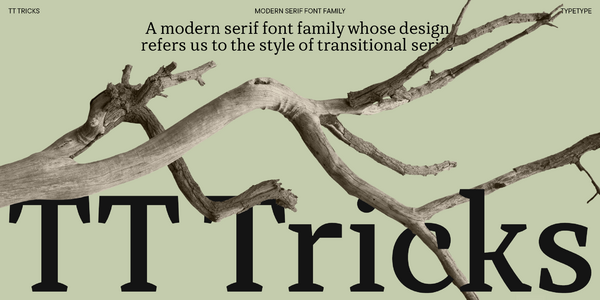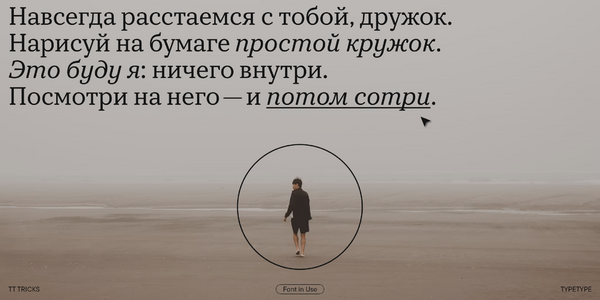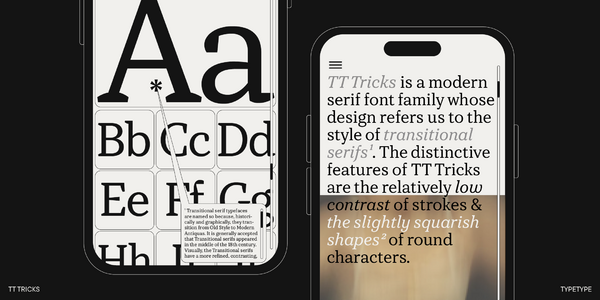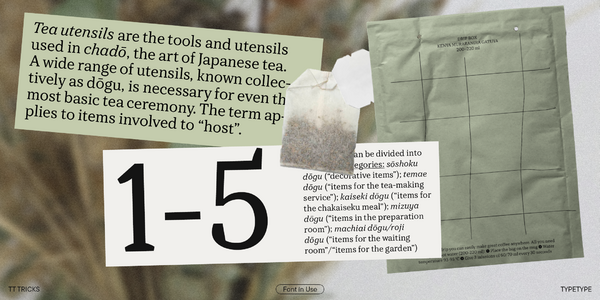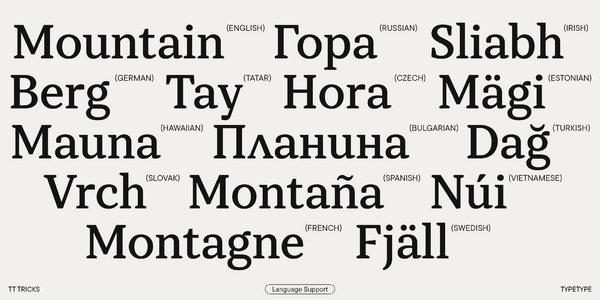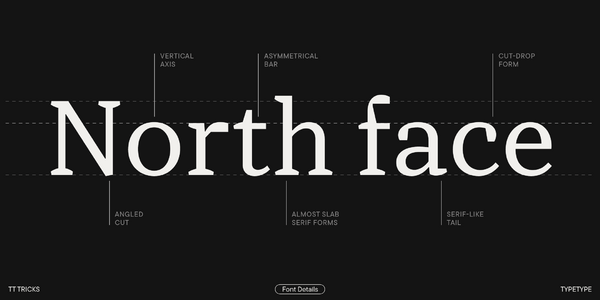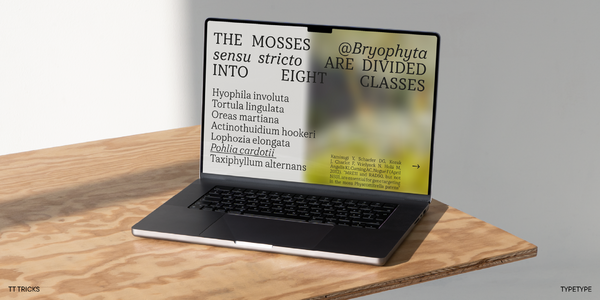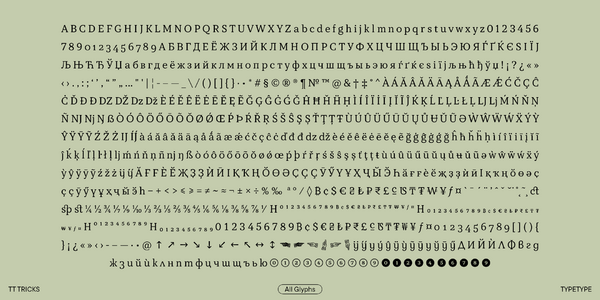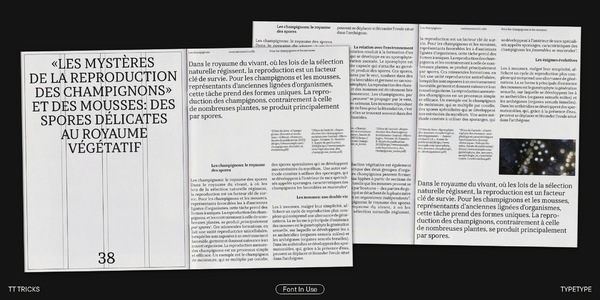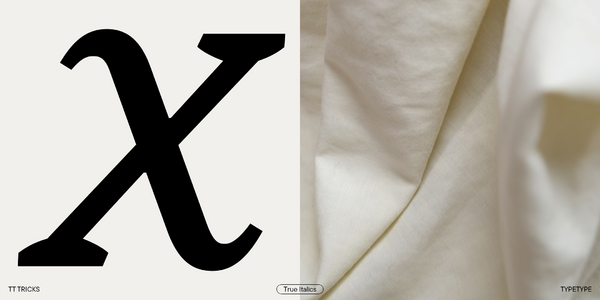
TT Tricks
TT Tricks — ТТ Трикс
Произносится «ТТ Трикс». «Tricks» — производное слово от trick, в переводе с английского «фокус». Буквы «TT» являются аббревиатурой названия компании.
TT Tricks — современная текстовая антиква со спокойным, элегантным, в меру строгим характером и подчёркнуто деловым настроением.
Вторая версия современной антиквы TT Tricks, свежая и переосмысленная
В 2018 году мы выпустили первую версию шрифтовой гарнитуры TT Tricks. В течение шести лет мы смотрели за примерами использования шрифтовой гарнитуры, а уже в 2023 году стали думать о том, как улучшить нашу антикву. В итоге мы отказались от трафаретной версии шрифта, перерисовали формы засечек, добавили новые тонкие начертания, а также сильно расширили знаковый состав в шрифте. Также мы сделали полностью новый курсив, который стал более изящным и самодостаточным.
Отличительными особенностями шрифтовой гарнитуры TT Tricks являются низкий контраст штрихов, чуть оквадраченные формы круглых знаков и подчёркнуто деловой характер. Первоначальная идея базируется на дипломной работе Софии Ясенковой, которая в качестве финального проекта выбрала шрифт для ежедневников.
TT Tricks в дизайне
О гарнитуре TT Tricks
Встречайте TT Tricks версии 2.000! Мы обновили эту сдержанную антикву: расширили кассовый состав и список поддерживаемых языков, добавили новые OpenType фичи и вариативные шрифты, а также усовершенствовали визуальные и технические характеристики гарнитуры.
TT Tricks — современная текстовая антиква, дизайн которой отсылает к стилю переходных антикв. Это шрифт со спокойным, элегантным и в меру строгим характером. Его отличительные особенности — сравнительно низкий контраст штрихов, крупные засечки, немного зауженные пропорции и слегка сквадраченные формы круглых знаков. Все это придает гарнитуре подчеркнуто деловое настроение.
Обновляя шрифт, мы сделали его более спокойным — снизили градус акцидентности, за счет этого он стал более текстовым. Следовательно, расширилась и сфера его применения. Кроме того, мы добавили 11 новых стилистических сетов и два вариативных шрифта, меняющихся по оси жирности — один для прямых весов и один для наклонных.
Также в версии 2.000 появились новые начертания — Thin, Thin Italic, ExtraLight, ExtraLight Italic, Medium, Medium Italic. Мы полностью перерисовали все контуры, изменили форму засечек и заново создали рисунок наклонных начертаний. Добавили 12 новых OpenType фич и расширили список поддерживаемых языков, в том числе на основе кириллицы. Полностью обновили кернинг и улучшили хинтинг. Серьезно расширили кассовый состав, в частности, дорисовали расширенную кириллицу и дополнили латиницу, расширили основной набор валют, добавили дроби и цифры для нумераторов / денумераторов.
TT Tricks — это настоящая классика: он выглядит сдержанно, при этом очень актуально. Благодаря этому сфера его применения очень широка. Этот шрифт раскрывает себя по-разному в зависимости от контекста, в котором он используется. В маленьком кегле он отлично читается, а в крупном размере раскрывает акцидентные детали и выглядит очень эстетично.
Обновленный TT Tricks — это:
• 20 начертаний: 9 прямых, 9 наклонных и 2 вариативных шрифта;
• 866 знаков в прямых и 858 знаков в наклонных начертаниях;
• 29 OpenType фич;
• Поддержка более 230 языков.
TT Tricks — бизнес-леди в мире антикв: деловая, современная, изящная!
Что изменилось в шрифте:
• Серьезно расширился кассовый состав: количество знаков увеличилось с 707 до 866 знаков в прямых и 858 знаков в наклонных начертаниях;
• Дорисована расширенная кириллица и дополнена латиница;
• Расширился основной набор валют, добавились дроби, цифры для нумераторов / денумераторов;
• Добавились новые начертания: Thin, Thin Italic, ExtraLight, ExtraLight Italic, Medium, Medium Italic. Количество начертаний выросло с 12 до 18;
• Увеличилось количество OpenType фич: с 17 до 29 в прямых и 28 в наклонных начертаниях;
• Появилось 2 вариативных шрифта, меняющихся по оси жирности: 1 для прямых весов и 1 для наклонных: